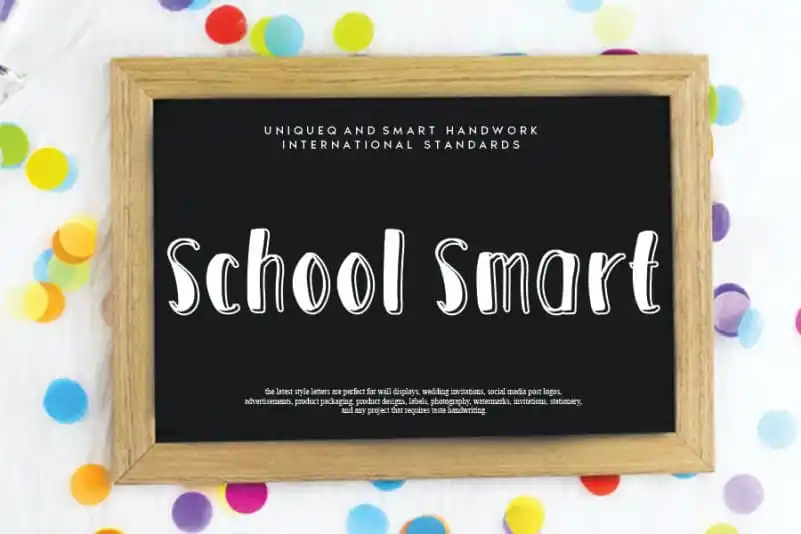
A School Smart Script Font é uma elegante fonte escrita à mão que mantém influências clássicas do calligrafia enquanto se torna contemporânea e atual. Este design cuidadosamente concebido pode conquistar qualquer projeto, oferecendo um toque único e sofisticado. Como uma verdadeira amiga da escola no mundo digital, a fonte School Smart Script é perfeita para dar um toque especial às letras e tornar seu trabalho ainda mais profissional. É ideal tanto para projetos de escrita normal quanto para design gráfico, garantindo que suas mensagens transmitem confiabilidade e estilo. Seja você um designer ou simplesmente quem escreve diariamente, a School Smart Script Font é sua nova amiga na jornada criativa. A fonte é perfeita para designers digitais que valorizam tanto o clássico quanto o moderno. Suas linhas sutis e delicadas transmitem confiança sem perder a elegância que fazem de qualquer projeto uma verdadeira arte. A School Smart Script Font, cuidadosamente concebida pela equipe da andikastudio, se torna uma fonte indispensável para aqueles que buscam um design simples, porém impactante em seus trabalhos.